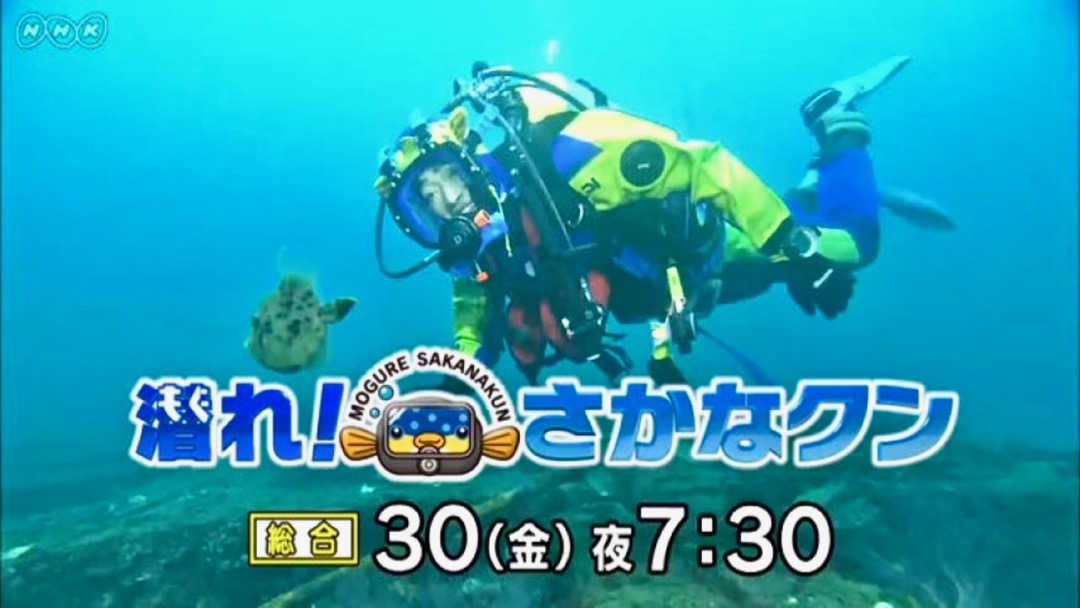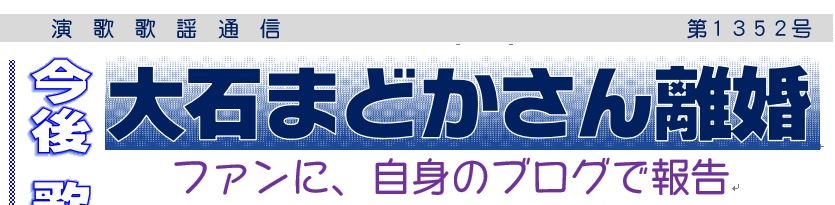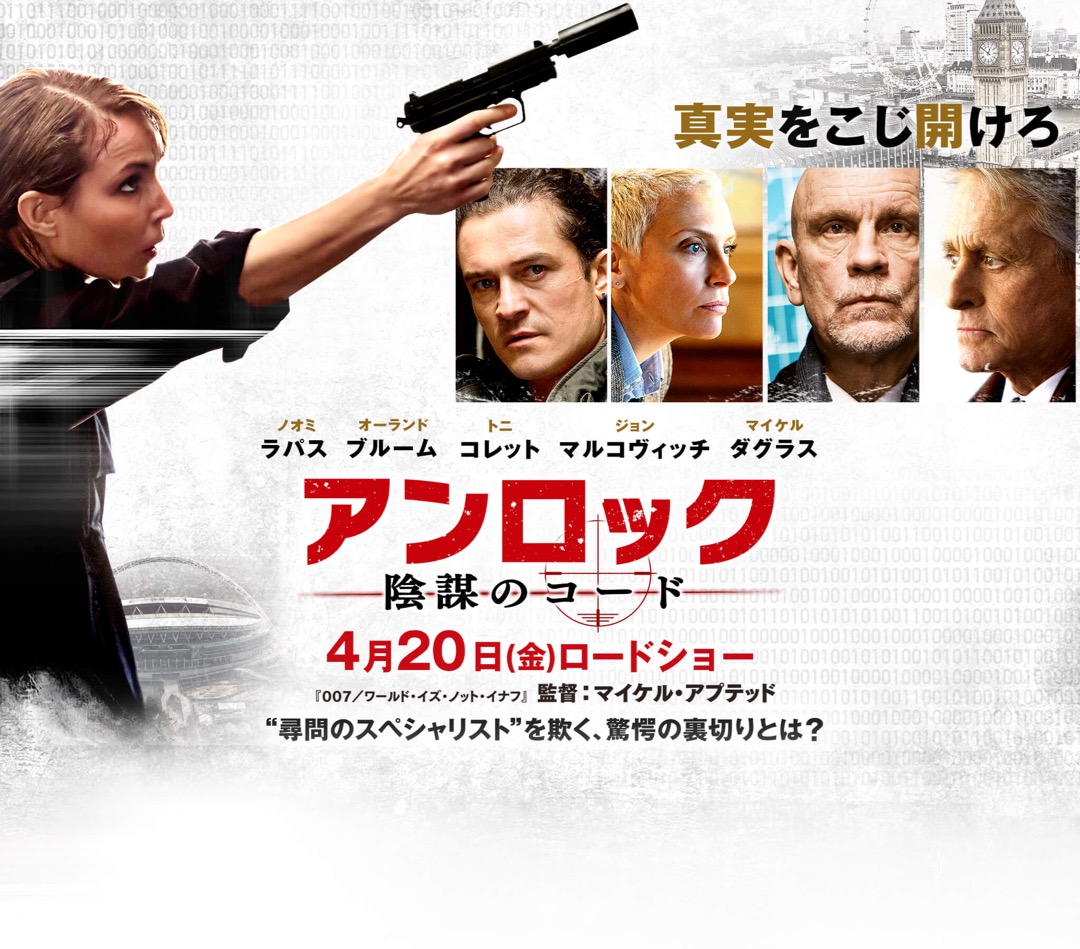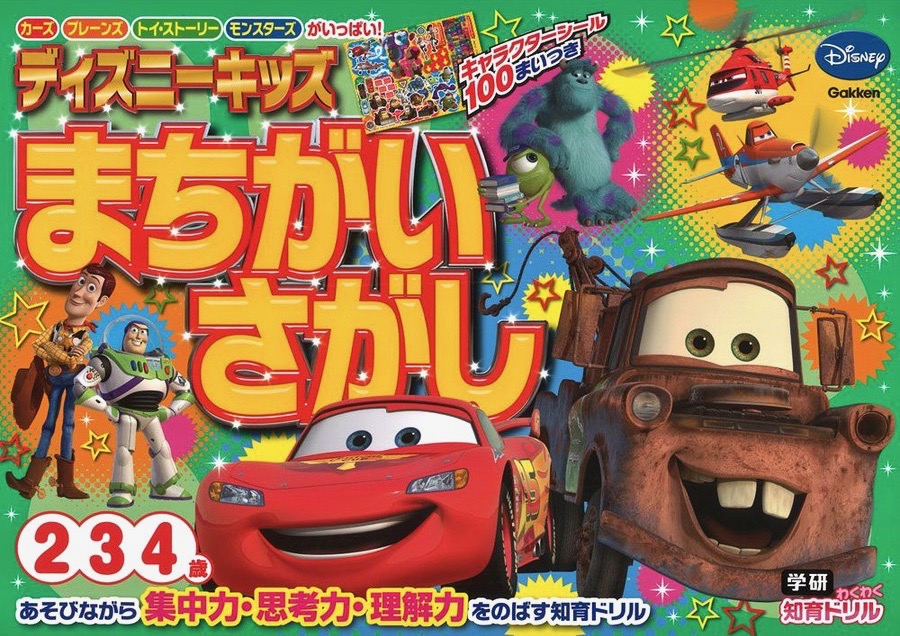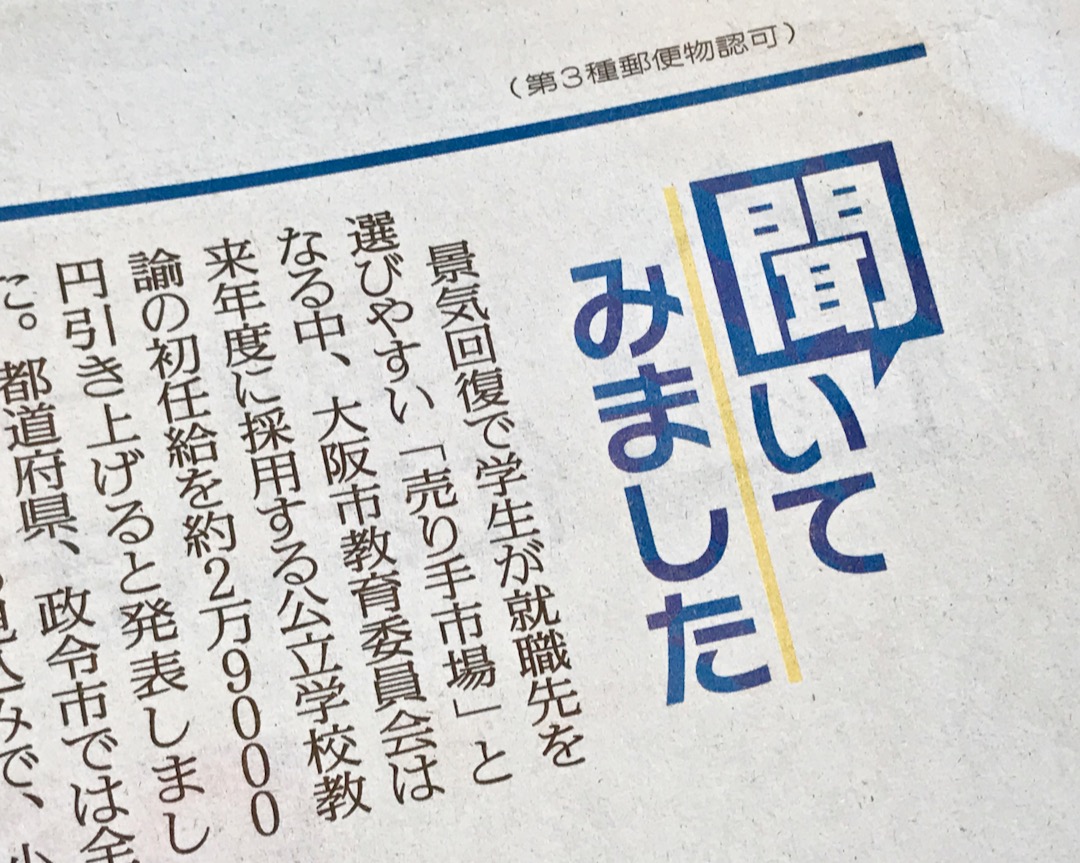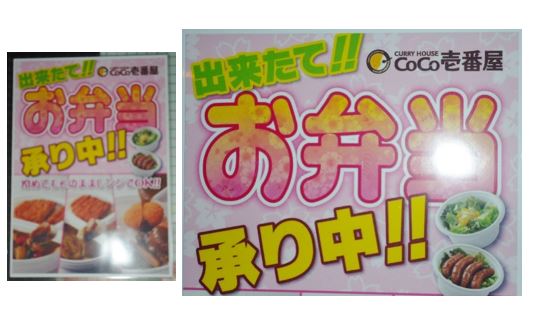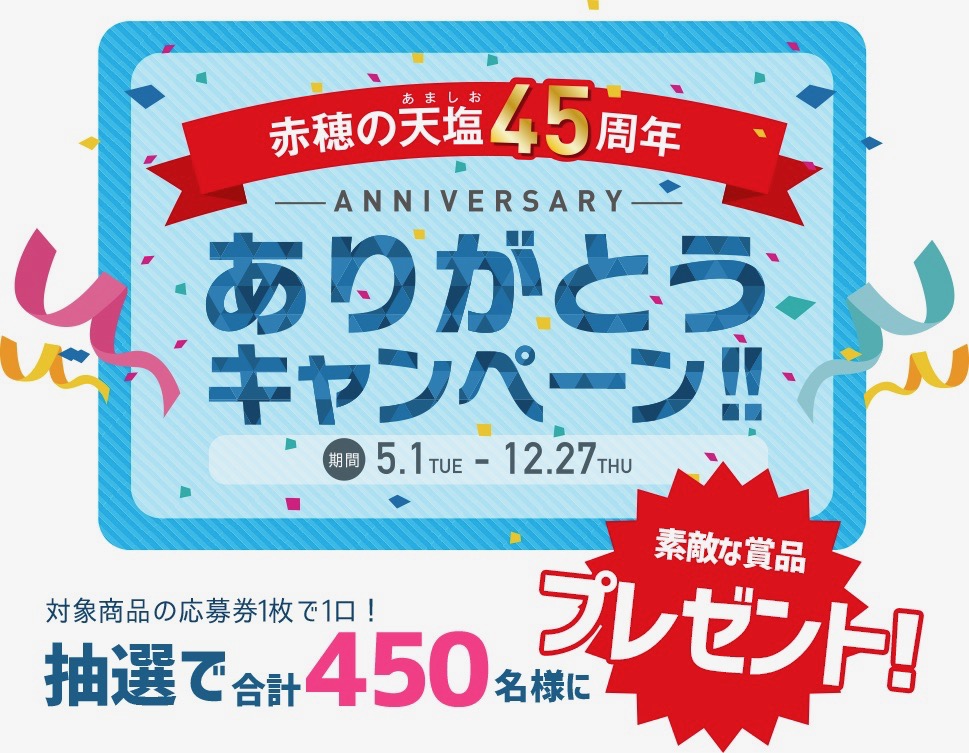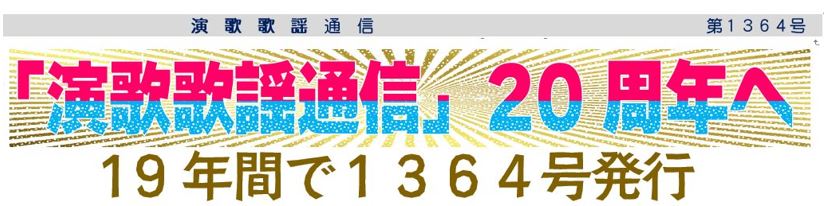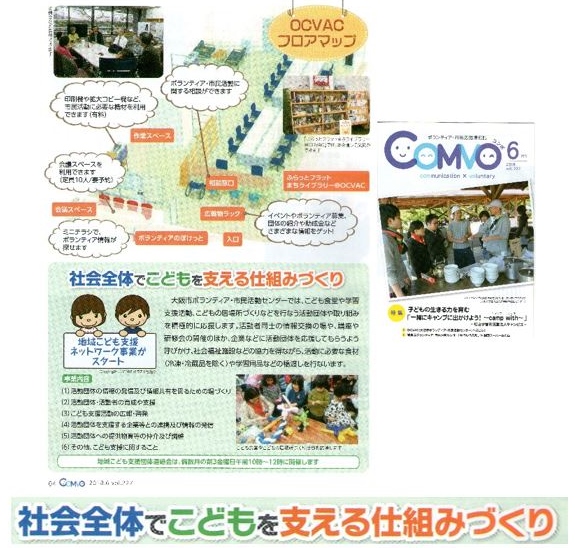
ピカチュウ可愛いから、また載せちゃうかな〜。
大阪市阿倍野区の超高層ビル・あべのハルカスの情報紙8月号で使用されています。
「ポケモンセンター」「ピカチュウのビンゴチャレンジ」「ファイアーアタック」のところです。
ち、ちいさい…。
書名:アンパンマン大図鑑
著者:やなせたかし、トムス・エンタテインメント
発行:フレーベル館
Instagramにも投稿しました、ローソンで見かけたニタラゴ使用例です。
「&」の特徴から、たぶんM社に提供されているタイプラボNですね。
アウトライン化して変にいじった使用例より、こういうシンプルな使用例が好みです(特にニタラゴに於いては)。
アウトラインを変にいじってデザインの品質を落とされると、オリジナル作者はがっくりします。
シンプルにこういう使い方は、ウレシイ…。
読売新聞、きのうの朝刊。
細めのニタラゴもキレイだと思う…。
大阪市版の子育て情報誌に掲載された近鉄百貨店のイベント広告です。
ピカチュウの下の「ポケモンセンター」です。ビカチュウかわいいので載せちゃいます(笑)
ピカチュウ、たしかにカワイイ!
6月25日に発売されたビッグコミックの13号。
これは広告。
大阪府堺市、さかいJOBステーションなどが主催の「さかいジョブマッチ交流会」の案内チラシです。A4判の裏面で大量に使用。
右側は部分拡大したものです。
大阪府の「府政だより」です。「もずやんの大阪ひとっとび」のタイトル
です。
ちなみに「もずやん」は、大阪府の広報担当副知事。と言っても、”府
の鳥”になっているモズで、府のマスコットキャラクターです。
かわいい広報担当副知事さんですね〜。
千原せいじのKids's World
同じ番組内…。
これも…。
大阪市立総合生涯学習センターの「出前講座」案内のパンフレット(A4判三つ折)です。
この書体、フォントワークスやモリサワからも販売されてますから、印刷物では、もうスタンダードな書体ですね…。